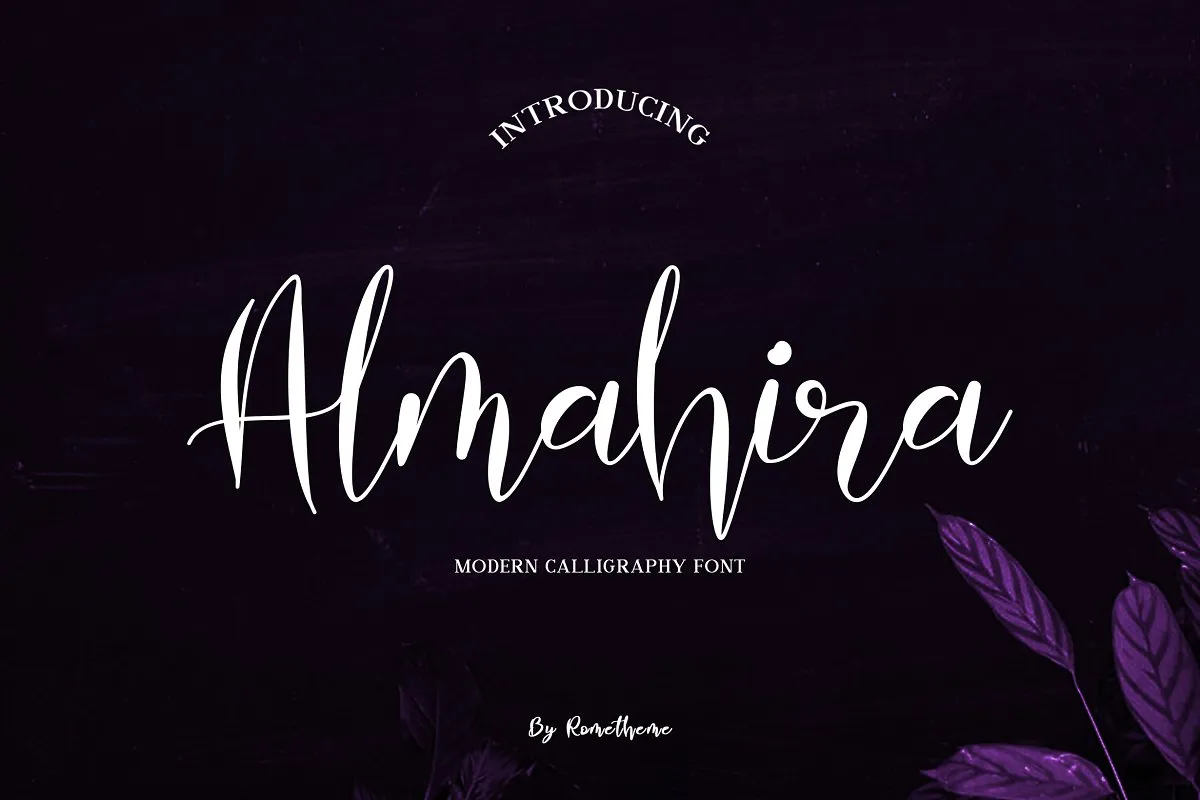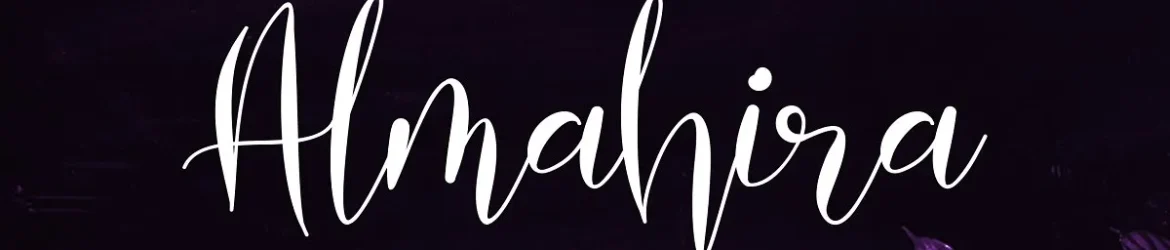
Almahira Script Font – Download Grátis
A Almahira Script Font é uma elegante tipografia para script criada por Rometheme que se destaca entre as demais. Se você busca estilos sofisticados e luxuosos, esta fonte não só atende às suas necessidades, mas oferece um pacote com tudo o que precisa em designs de papel ou digital. Esta fonte moderna para chamigrafia traz um toque elegante a qualquer projeto – seja ele uma invitacional luxuosa, designs para redes sociais estilosos ou até mesmo estampas de cartão de visita elegantes. Almahira Script é perfeita tanto para quem está buscando dar um toque criativo às suas criações digitais quanto para aqueles que desejam uma opção sofisticada em impressões. Seja você um designer gráfico, um editor de conteúdo digital ou até mesmo um amante de design pessoal, a Almahira Script é certamente o tipo certo para complementar seu estilo único e agregar elegância sem esforço ao seu trabalho.